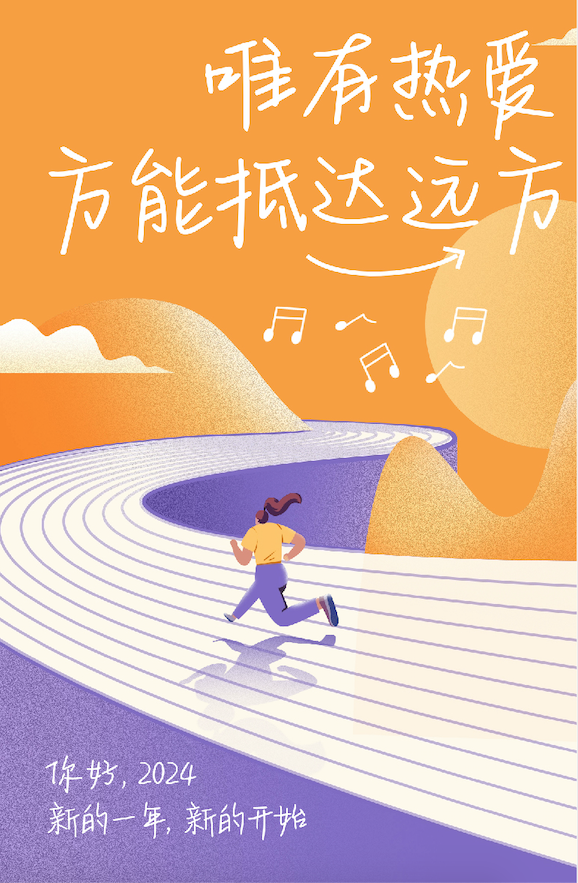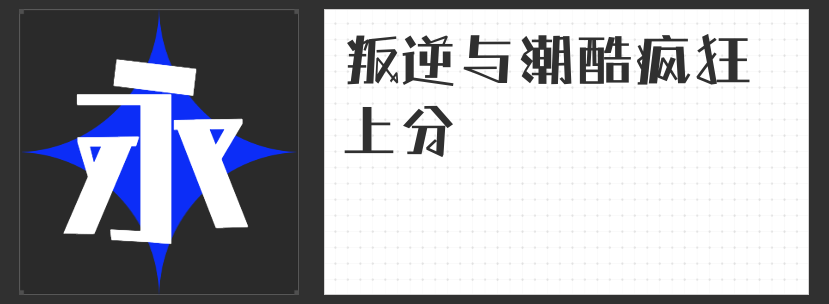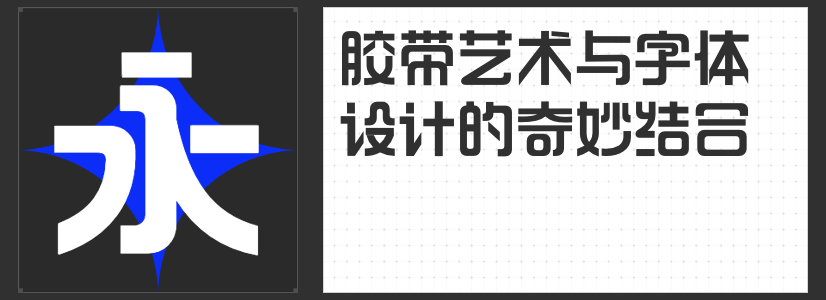
艺术展览的字体魔法:为展览增添无限创意与氛围
在艺术展览的浩瀚画卷中,字体的选择如同精心布置的展陈元素,不仅承载着信息的传递,更是展览主题与氛围的直观展现。今天,就推荐四款能在艺术展览设计中大放异彩的字体。
1. 造字侠醉春风简繁 苍劲
这款字体以其独特的苍劲笔触,成为诠释传统文化艺术展览的不二之选。无论是书法展、国画展还是古典文物展,造字侠醉春风简繁 苍劲都能完美融合,营造出一种穿越时空的文化氛围,让观者在字里行间感受历史的厚重与艺术的魅力。
2. 造字侠选地铁修悦体 大黑
字体笔画简洁而富有力量感,特别适合现代艺术展览的标题或重点信息呈现。在装置艺术、数字艺术或前卫艺术展览中,这款字体能迅速抓住观众的视线,与展览的先锋性、创新性相得益彰,共同构建出独特的视觉体验。
3. 字恋狂拙黑简
这款字体以其狂放不羁的特质,成为表达个性与创意的艺术展览的理想伴侣。在独立艺术家作品展、涂鸦艺术或实验性艺术展览中,字恋狂拙黑简能够完美诠释艺术家的独特视角与创作理念,激发观众的无限遐想与共鸣。
4. 高手兵克清秀体
其清秀俊逸的手写线条,为那些追求高雅、清新艺术氛围的展览增添了一抹亮色。在摄影展、花卉展或茶文化展览中,高手兵克清秀体能够以其独特的韵味,营造出一种宁静致远的艺术空间,让观众在欣赏作品的同时,也能感受到一份心灵的洗涤与升华。
综上所述,这四款字体各具特色,无论是古典与现代的交融,还是个性与创意的碰撞,亦或是清新与高雅的展现,它们都能在艺术展览设计中找到属于自己的舞台,为展览增添无限的光彩与深度。